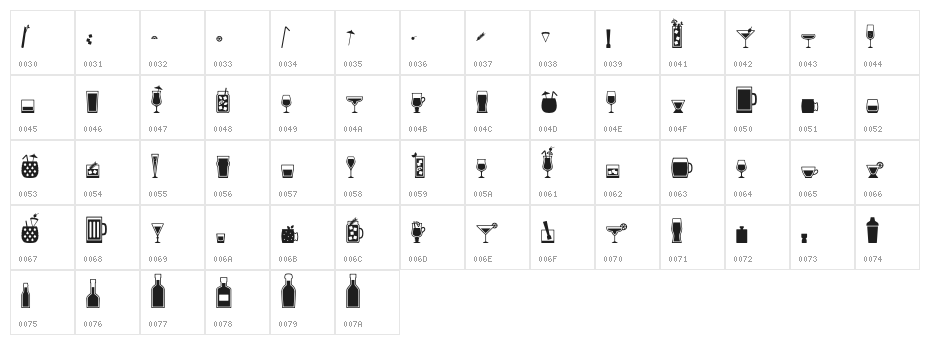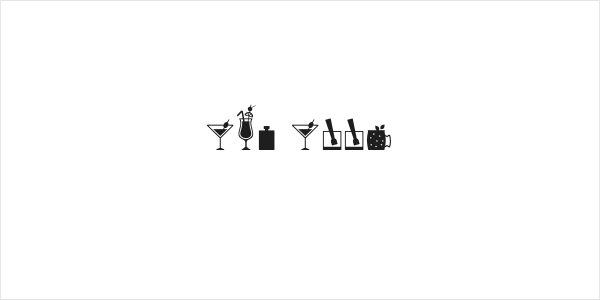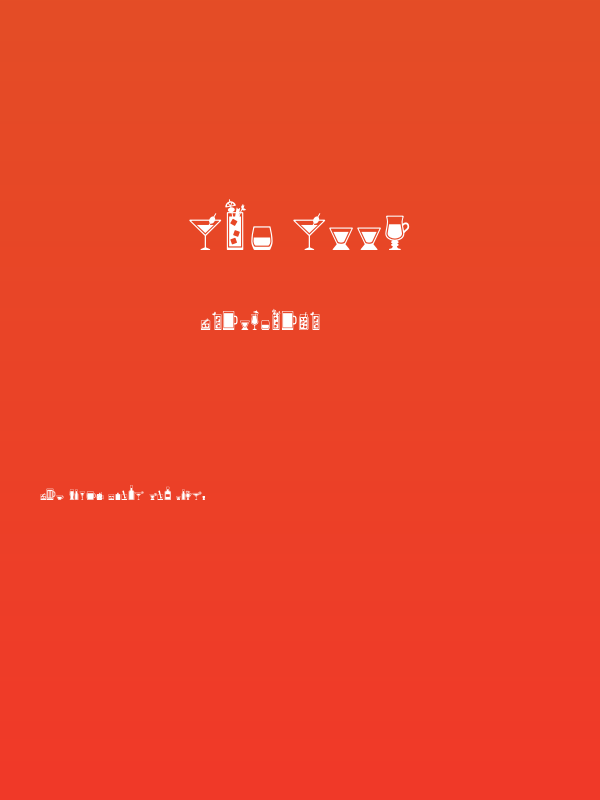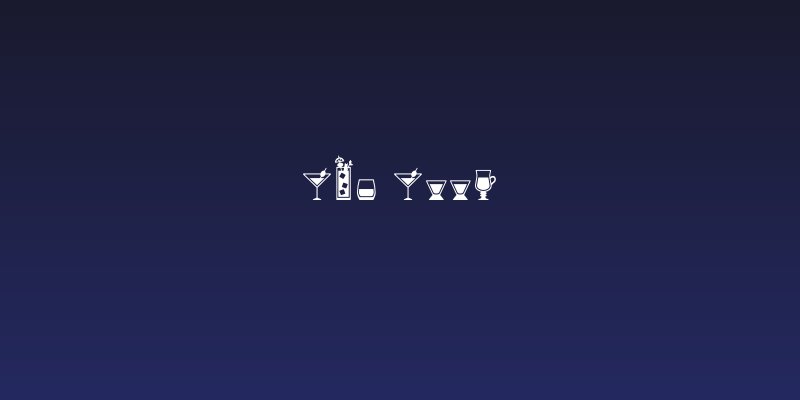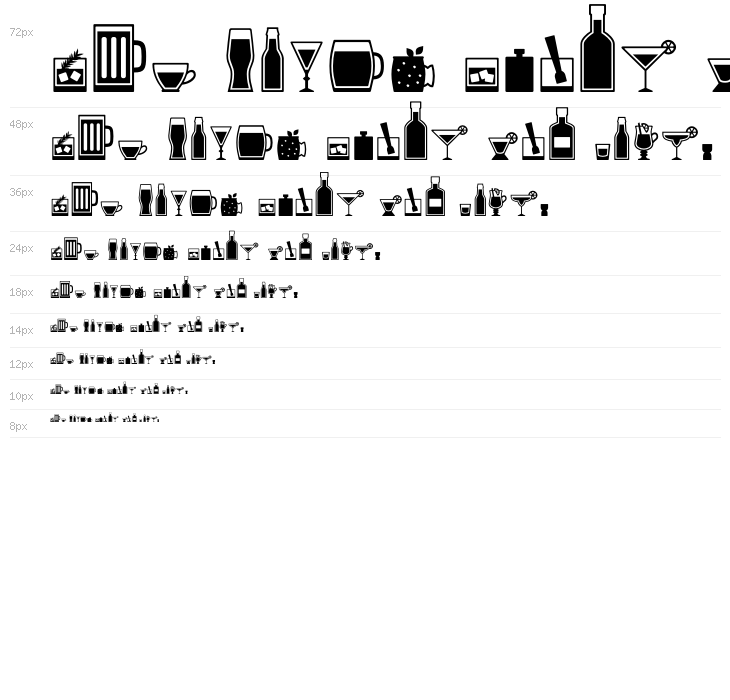
Bar Book Font
| Caso d'uso | Logos, Menus, Branding |
| Progetti proposti | Ideal for use in bar menus, cocktail recipe books, event invitations, and branding for beverage companies. |